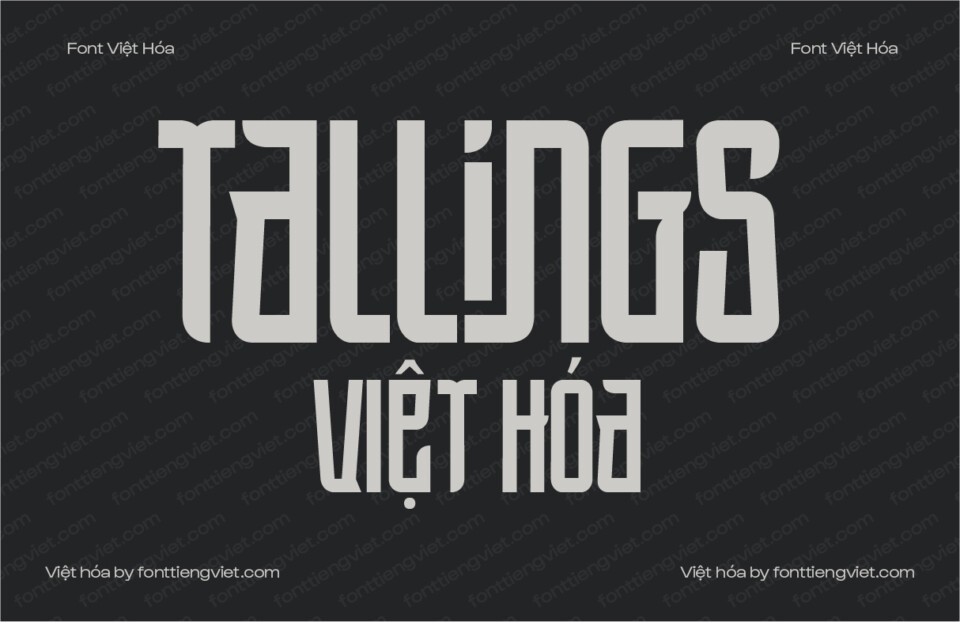
Font Việt hóa 1FTV Tallings
Giới thiệu về Font Việt hóa 1FTV Tallings trong thiết kế
Trong thế giới đồ họa hiện đại, việc lựa chọn một bộ Font Miễn Phí chất lượng là yếu tố then chốt để tạo nên sự khác biệt. Font Việt hóa 1FTV Tallings nổi lên như một lựa chọn hoàn hảo cho những ai yêu thích phong cách thanh mảnh, cao ráo và đầy tinh tế. Đây là bộ font được tinh chỉnh kỹ lưỡng để phù hợp với bảng mã tiếng Việt, giúp người dùng không còn lo lắng về lỗi hiển thị dấu khi soạn thảo văn bản hay làm thiết kế.
Đặc điểm nổi bật của Font Việt hóa 1FTV Tallings
Điểm ấn tượng nhất của bộ font này chính là cấu trúc ký tự hẹp (condensed) nhưng vẫn đảm bảo độ thoáng đãng cần thiết. Font Việt hóa 1FTV Tallings mang lại cảm giác sang trọng, thường được ứng dụng trong các bìa tạp chí, tiêu đề phim hoặc menu nhà hàng cao cấp. Với các đường nét dứt khoát và tỉ lệ hình khối chuẩn xác, font chữ này giúp các thiết kế trở nên chuyên nghiệp và hiện đại hơn bao giờ hết.
Cách ứng dụng Font Việt hóa 1FTV Tallings hiệu quả
Để tận dụng tối đa vẻ đẹp của Font Việt hóa 1FTV Tallings, các bạn học sinh và giáo viên có thể sử dụng làm tiêu đề cho các bài thuyết trình PowerPoint hoặc poster sự kiện trường học. Khi kết hợp cùng những màu sắc tối giản như đen, trắng hoặc vàng đồng, font chữ này sẽ tạo nên hiệu ứng thị giác mạnh mẽ. Lưu ý nhỏ là bạn nên giãn cách dòng (line spacing) hợp lý để các ký tự cao không bị chồng lấn vào nhau.